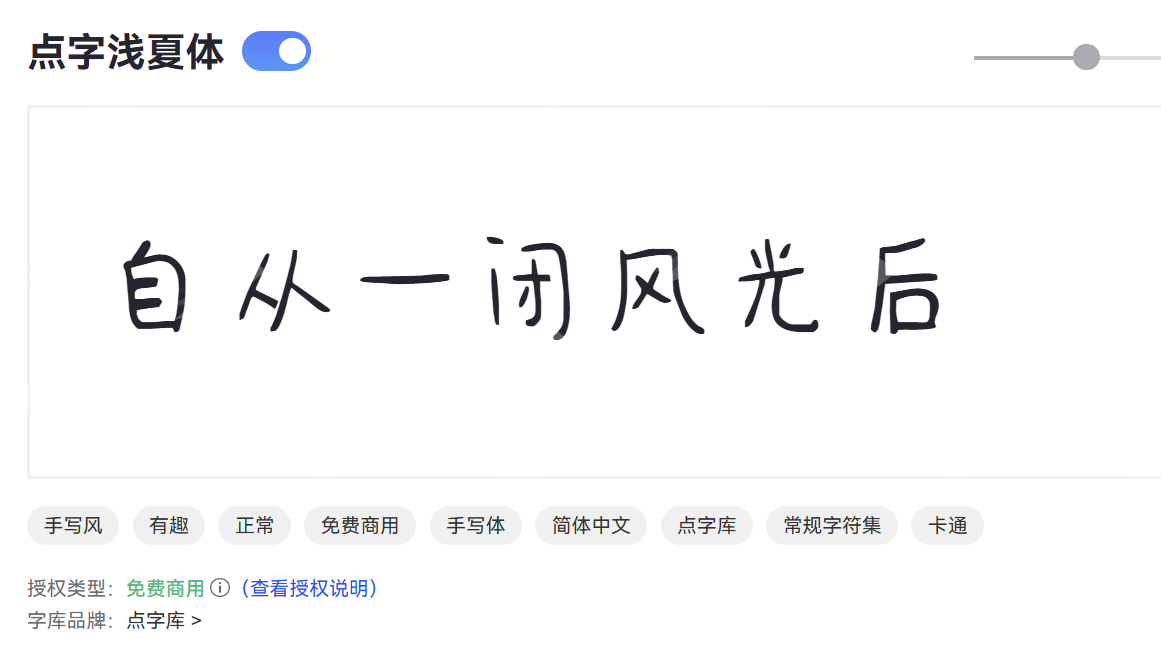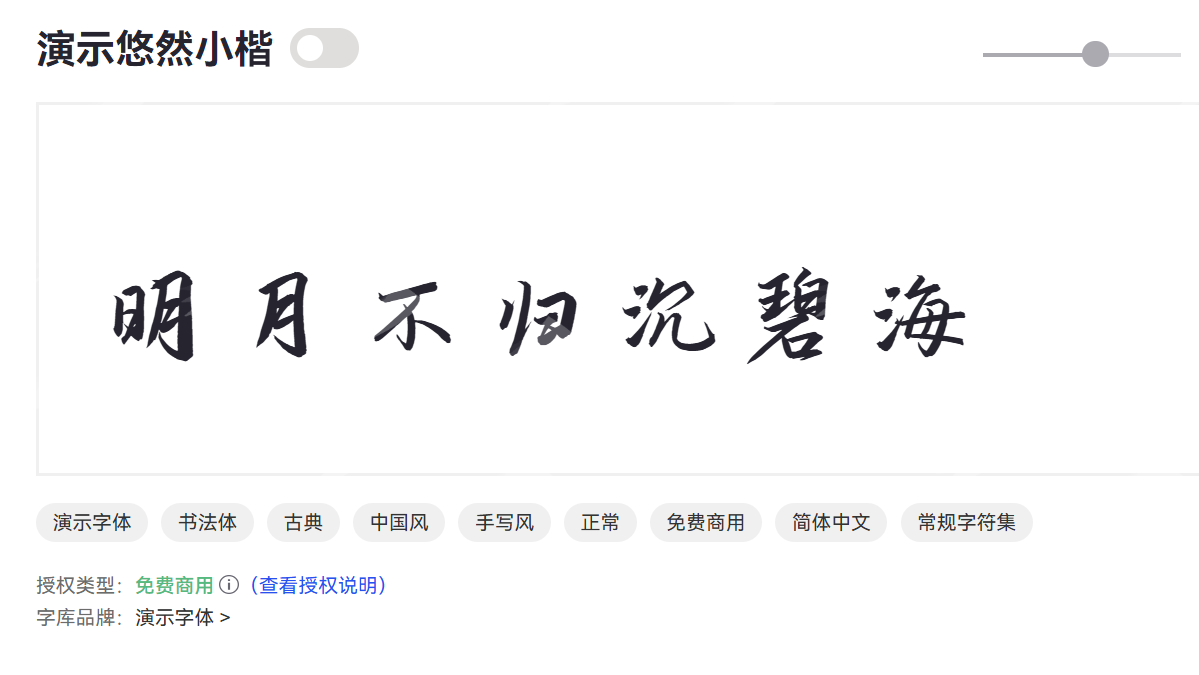
签名字体大全,7 款好看的签名字体推荐
当你在重要的文件上,或者在你的作品上签下自己的名字时,不是随意的签写,而是经过精心设计的、充满艺术韵味的字体,一定会让人印象深刻!本文就给大家介绍一些好看的签名字体,除了授权商用的,还有可以免费商用的,一起来看看吧。
一、 签名字体是什么样的一类字体
顾名思义,就是专门为签名设计的字体。与我们日常书写的印刷体或手写体不同,签名字体更注重字体的艺术表现力和独特性。它们通常模仿了书法艺术的流畅、飘逸、洒脱,又融入了现代设计的简洁、力量和美感。
签名字体的特点:
- 艺术性强: 它们通常具有书法般的笔触变化,流畅的线条,以及独特的造型,能够展现出写书人的个性和情感。
- 独特性高: 每一款签名字体都有其独特的风格,有的飘逸如云,有的刚劲有力,有的优雅细腻,有的活泼可爱,能够满足不同人群的个性化需求。
- 辨识度高: 虽然艺术化,但好的签名字体依然能够保证一定的辨识度,让看到签名的人能够大致识别出名字。
- 设计感足: 许多签名字体融合了现代设计理念,线条的粗细、字体的倾斜、笔画的连接都经过巧妙设计,使其在视觉上更具冲击力。
- 情感表达: 签名是个人情感和个性的直接流露,签名字体能够更好地放大和呈现这种情感,让签名充满生命力。
二、可以免费商用的签名字体
平方迎风体
平方迎风体是一款设计风格独特、充满动感的字体。它将硬朗的几何方形结构与流畅、飘逸的笔触相结合,仿佛在平方的画布上,迎风舒展,展现出一种既稳健又充满活力的视觉效果,适合需要强调力量、速度或现代感的场景。
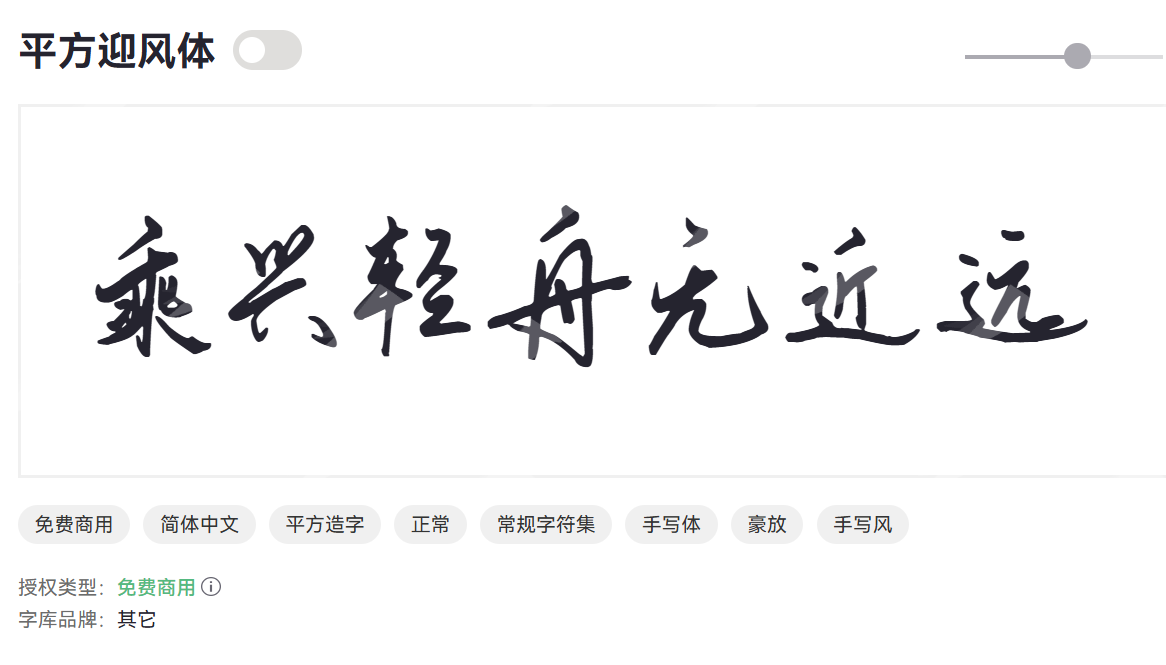
字体特点
- 笔画主体为方正结构,但转折和收尾处常带有飞白或舒展的笔触。
- 整体字形仿佛在运动中,充满张力与速度感。
- 视觉冲击力强,带有鲜明的现代设计美学。
点字浅夏体
点字浅夏体是一款清新、自然的字体,仿佛将夏日清晨的微风和阳光融入字里行间。它以轻盈、柔和的笔触,营造出一种宁静、舒适、带有淡淡文艺气息的视觉感受,非常适合用于传达夏日的美好、清新或自然的主题。
字体特点
- 线条纤细,转折处圆润,整体感觉轻快、舒展。
- 字形不刻意追求工整,带有手写般的随性与舒适感。
- 适合搭配清新、明亮的色彩组合。
演示悠然小楷
演示悠然小楷是一款优雅、精致的仿小楷字体。它继承了传统小楷的秀丽、流畅和韵味,同时在结构和笔画上进行了现代化的调整,这款字体适合用于需要展现细腻、文雅、有文化底蕴的场合。
字体特点
- 线条纤细,如行云流水,转折处含蓄有力。
- 字形紧凑而舒展,布局匀称。
- 在保证艺术性的同时,兼顾了信息传达的清晰度。
三、需要授权商用的签名字体
默陌静斋笔迹
默陌静斋笔迹是一款模仿文人墨客书写笔迹的艺术字体。它追求一种静谧、淡泊、内敛的书写风格,笔画不张扬,结构自然,仿佛是一位书画家在静思时留下的墨痕。
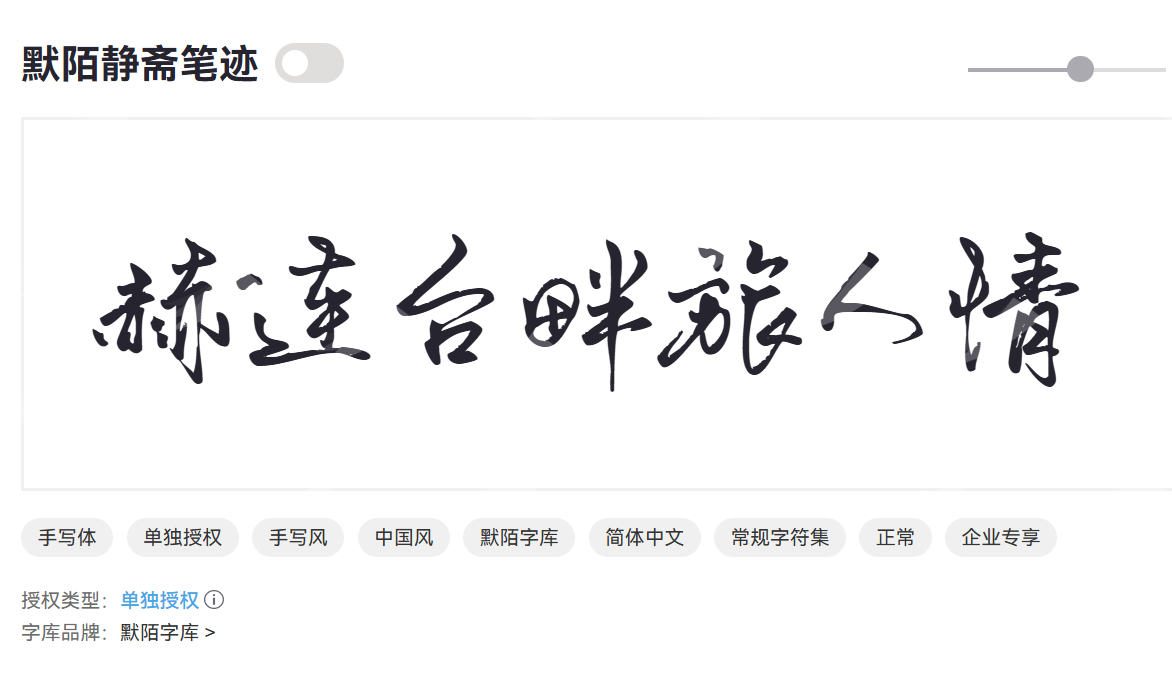
汉仪李李体
汉仪李李体是一款现代艺术字体。它巧妙地融合了手写体的自然流畅与现代设计的简洁利落,字形活泼而富有表现力,兼具优雅与俏皮感,能够为品牌和设计带来独特的视觉标识和鲜明的个性。
点字手写童真体
点字手写童真体是一款专为儿童设计的手写风格字体。它模仿了儿童天真烂漫的笔迹,笔画圆润、形状稚拙、结构随意,充满了孩童的纯真与想象力。这款字体旨在为儿童产品和内容营造一个充满欢乐、安全、富有童趣的视觉环境。
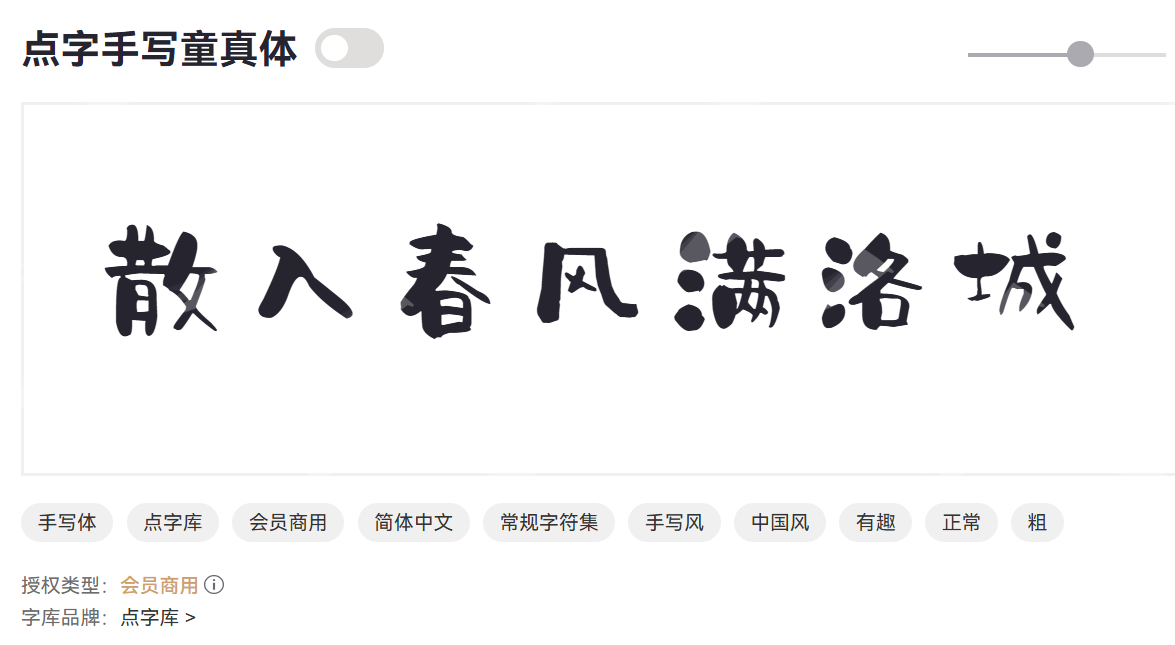
孤独的流浪诗
孤独的流浪诗是一款极具艺术感和故事性的字体。它以一种略带忧郁、自由不羁的笔触,仿佛是流浪者在旅途中写下的诗篇,充满了情感的表达和独特的个人印记。这款字体适合用于需要传达深刻情感、艺术探索或独特人生态度的设计。